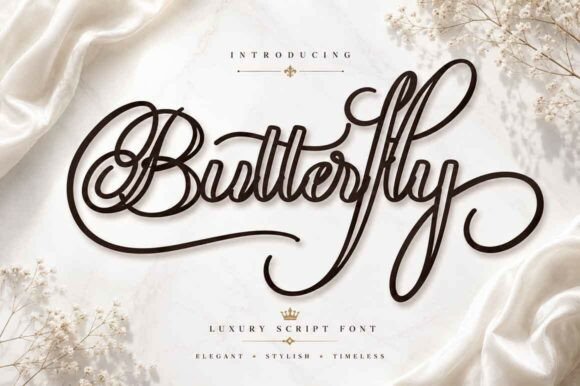
Butterfly Outline
Butterfly Outlineのような高品質の素材をお探しの場合、このプレミアムパッケージはクリエイティブなプロジェクトに素晴らしい選択です。
POD(オンデマンド印刷)製品、結婚式の招待状、またはソーシャルメディアのグラフィックを作成している場合でも、Butterfly Outlineは理想的です。